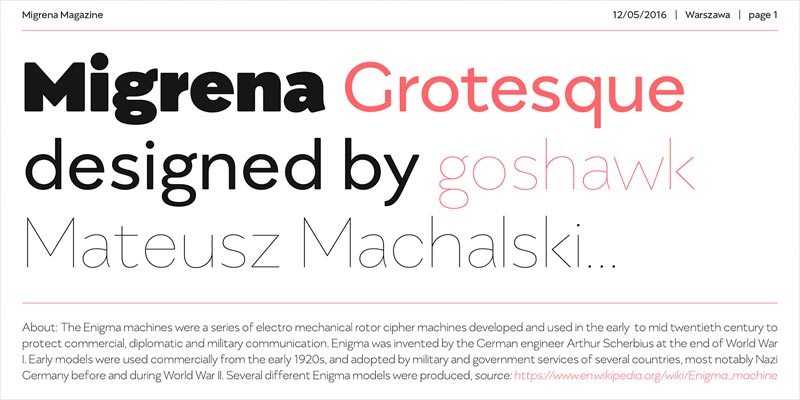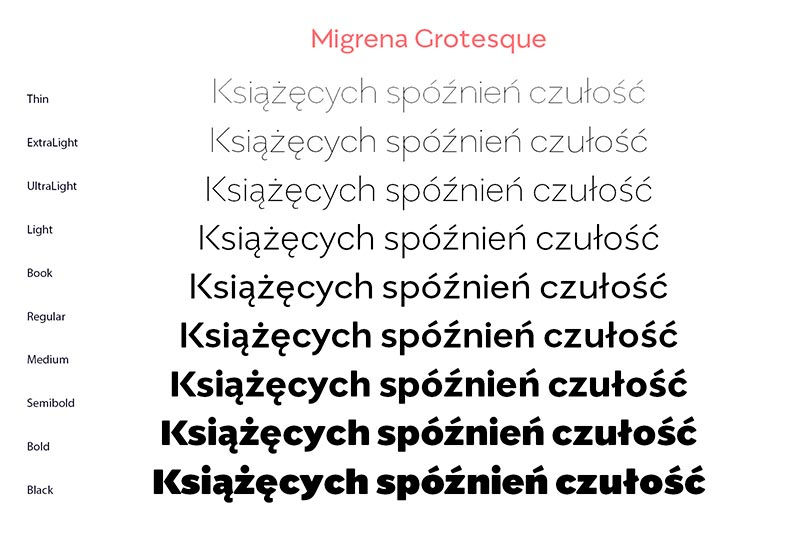
Font Migrena Grotesque
Zakupiliśmy rodzinę fontów geometrycznych Migrena Grotesque, która składa się z 18 odmian. Autorem jest Mateusz Machalski. Na uwagę zasługuje bardzo duży kontrast pomiędzy najlżejszą a najcięższą odmianą, pozwalający uzyskać ciekawe efekty typograficzne.